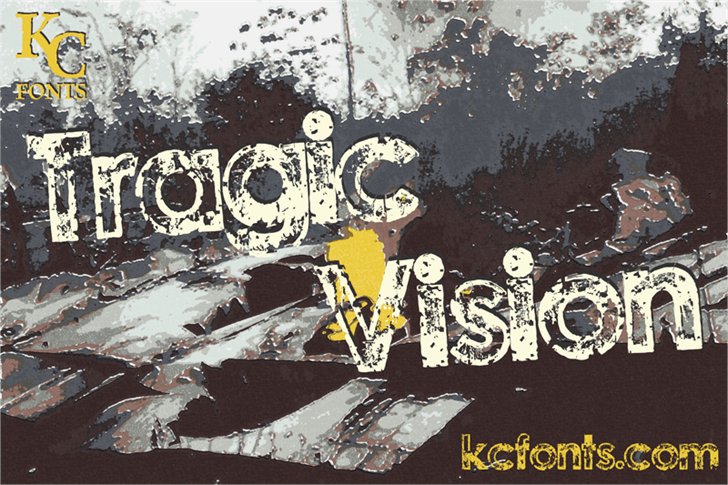
A fonte Tragic Vision é uma escolha perfeita para designers que valorizam a simplicidade e o estilo moderno. Seja você criando um site dinâmico, uma identidade de marca sofisticada ou até mesmo adesivos práticos para sua garagem, esta fonte sans serif oferece um equilíbrio perfeito entre elegância e praticidade. Com origem em mãos do designer Hamilton, Tragic Vision combina linhas retas com detalhes sutis que dão uma sensação de calma. Seu uso eficiente dos espaços pode dar ao seu design um toque casual sem perder o foco e a seriedade necessários para um layout elegante. Esta fonte é particularmente adequada para projetos digitais, como websites ou designs digitais. Ela mantém um contraste visual sóbrio que se adapta perfeitamente a muitas paletas de cores existentes, permitindo uma experiência de leitura confortável e profissional em qualquer tela. Com apenas duas linhas curtas nesta descrição, Hamilton demonstrou uma entusiasmo genuíno por sua fonte. Tragic Vision não é apenas um recurso gráfico mais uma vez, mas também parte do espírito jovial e ousado que caracteriza a criatividade moderna.